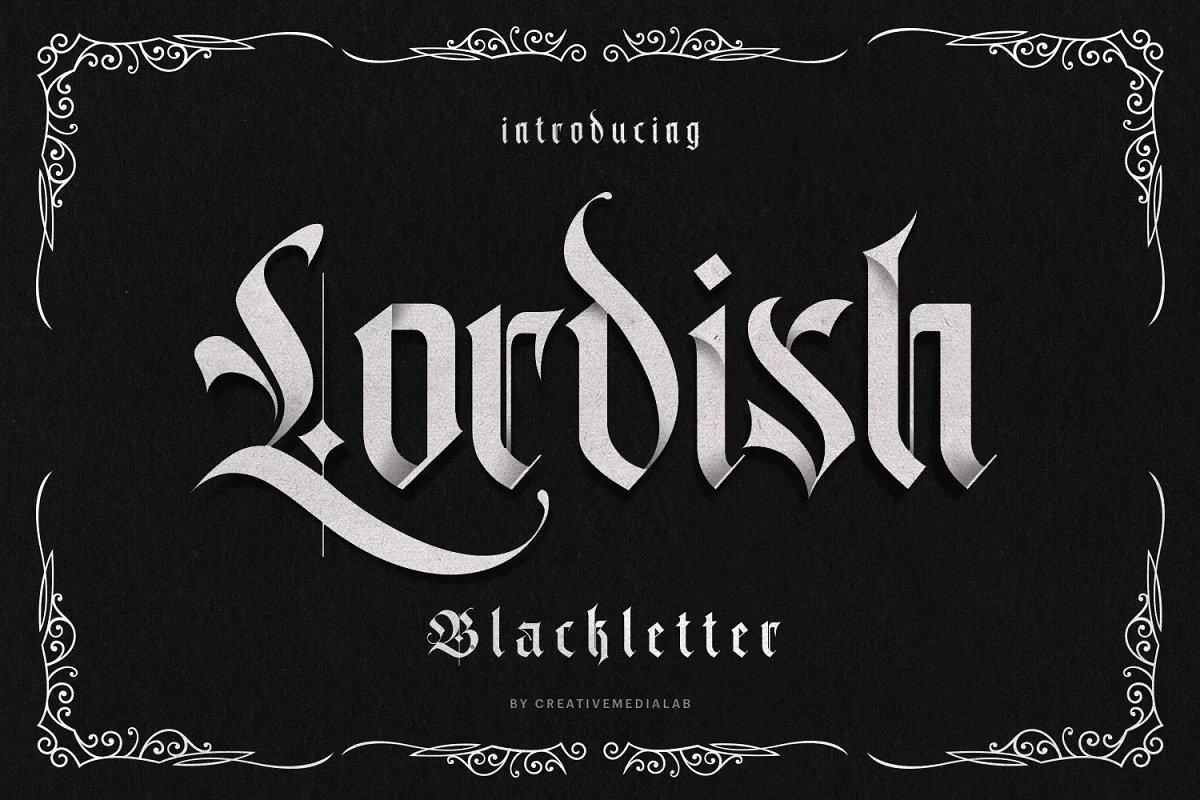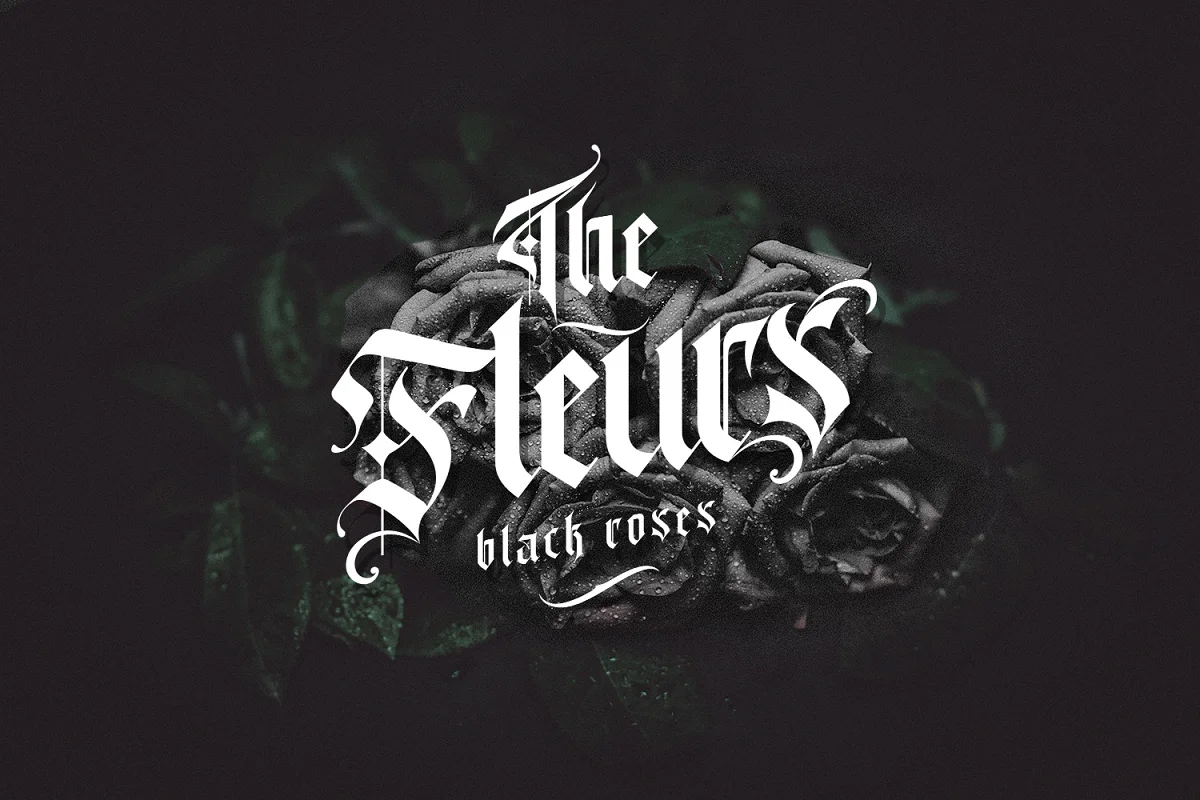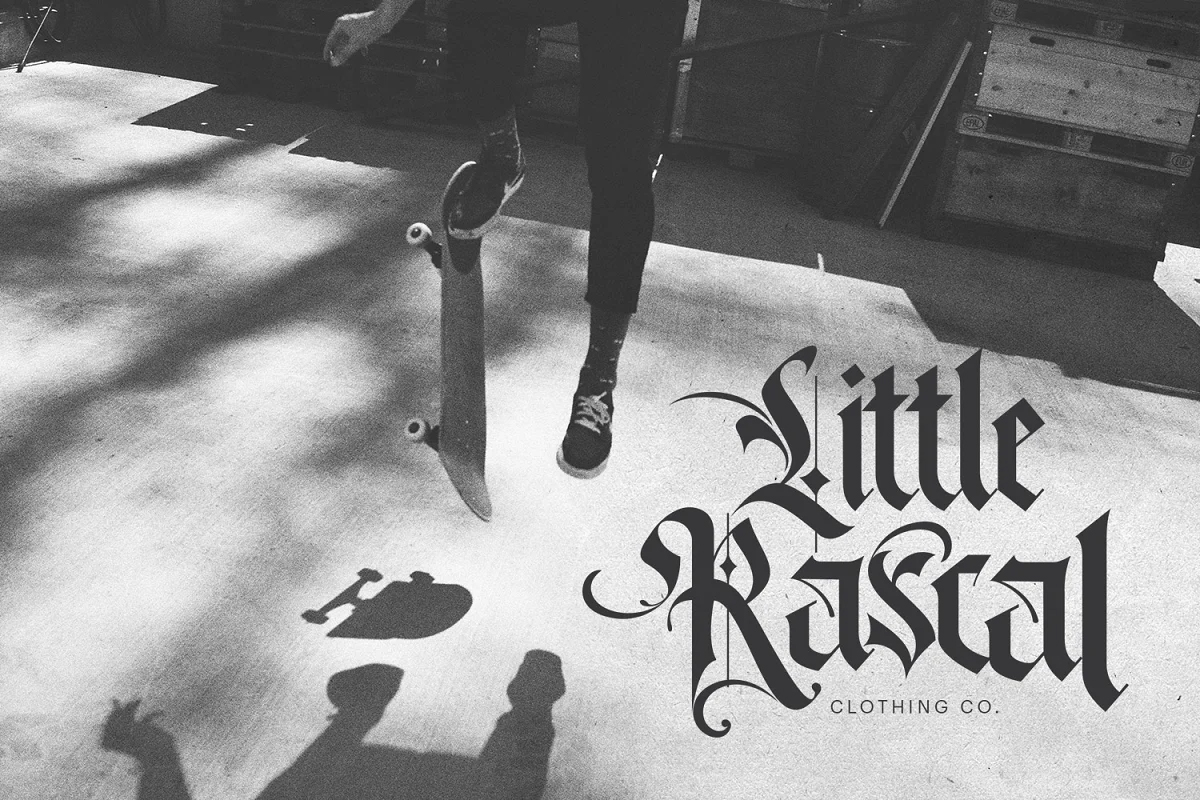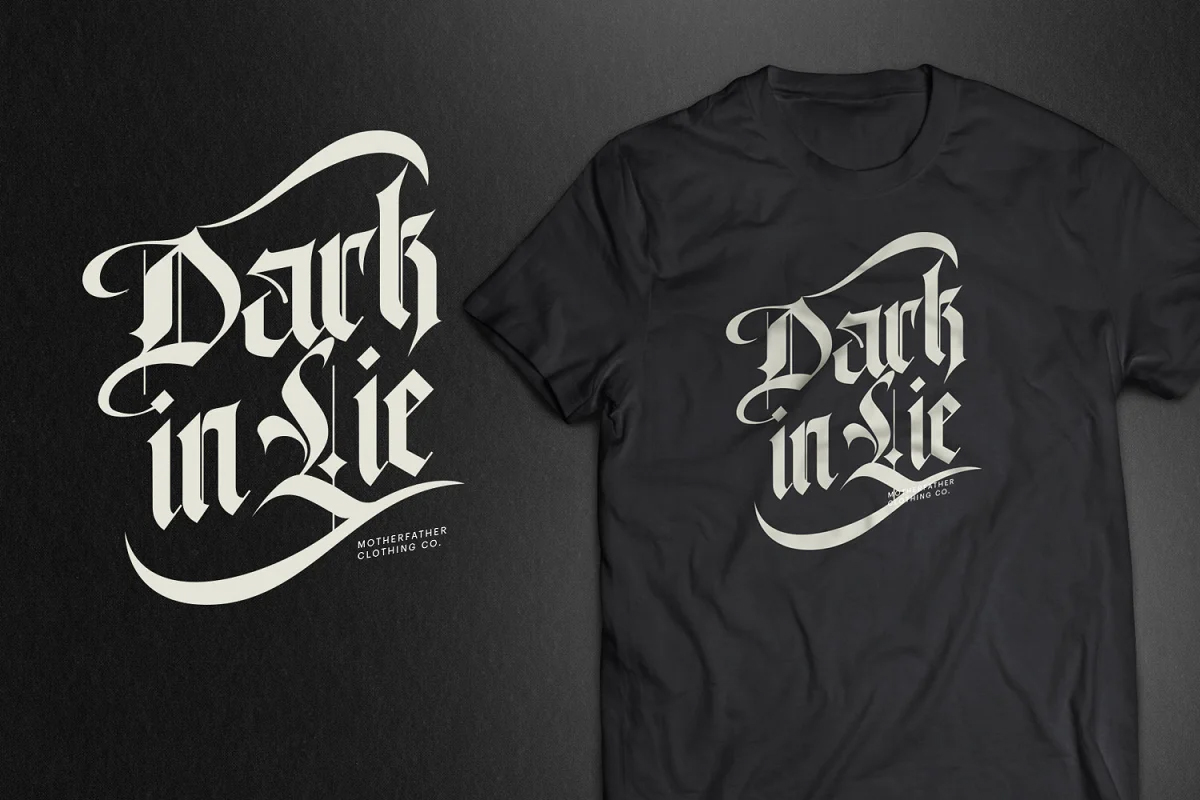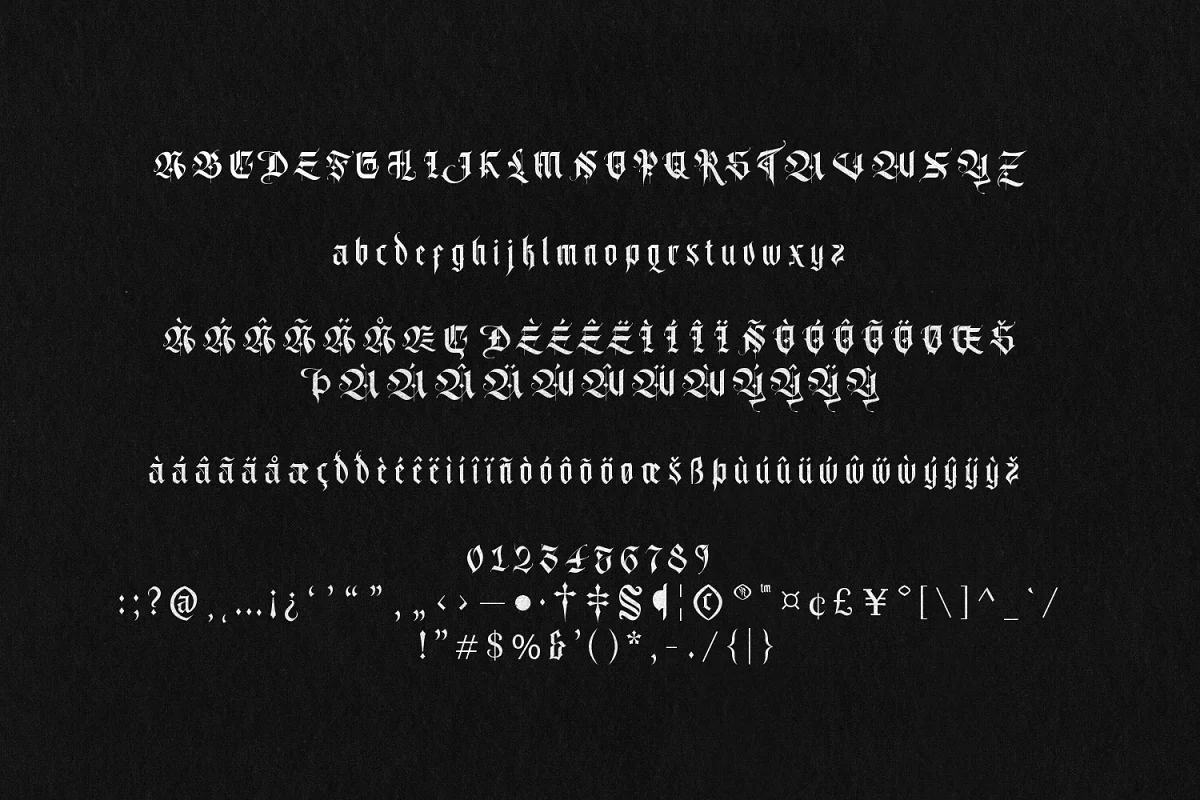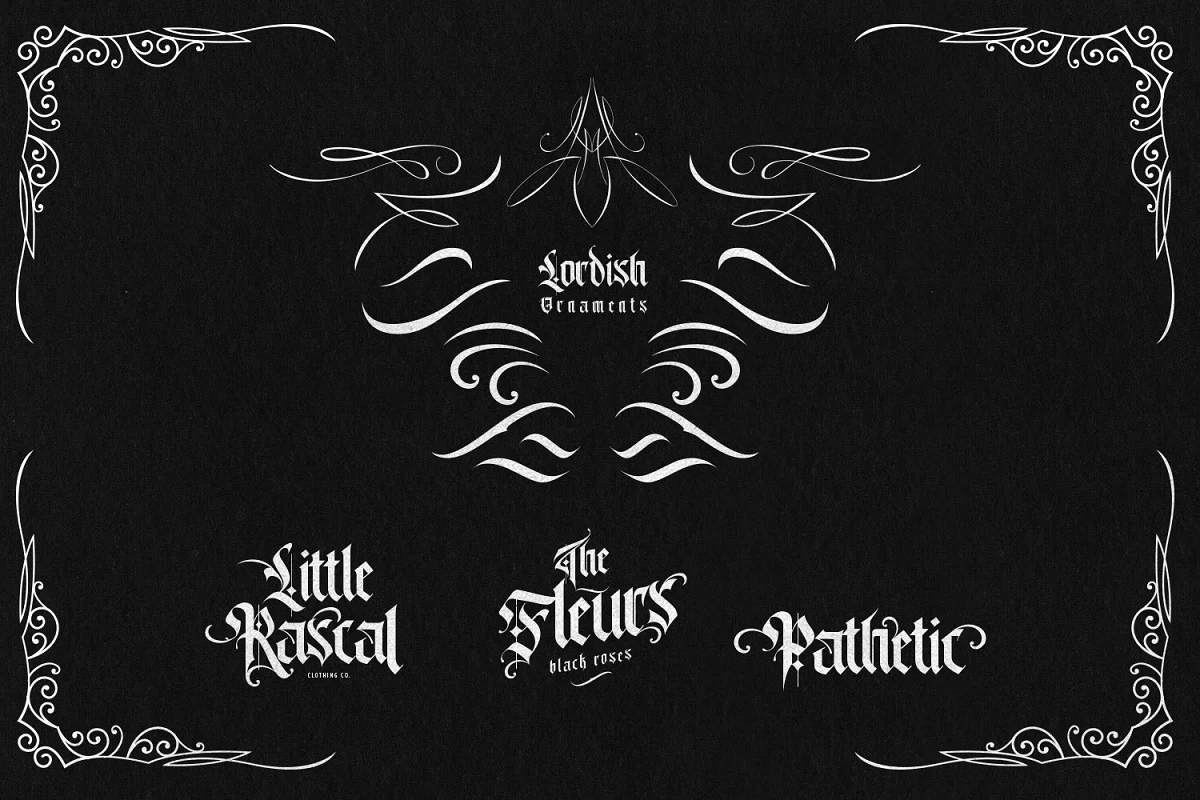
Font Lordish Việt Hóa – Font phù hợp cho tattoo
Font Lordish Việt Hóa – Lordish Blackletter, một blackletter độc đáo cho thiết kế của bạn. Bao gồm chữ hoa, chữ thường và dấu chấm câu và các ký tự quốc tế. Tốt cho font chữ hiển thị, font chữ tattoo hoặc các phong cách khác của bạn.